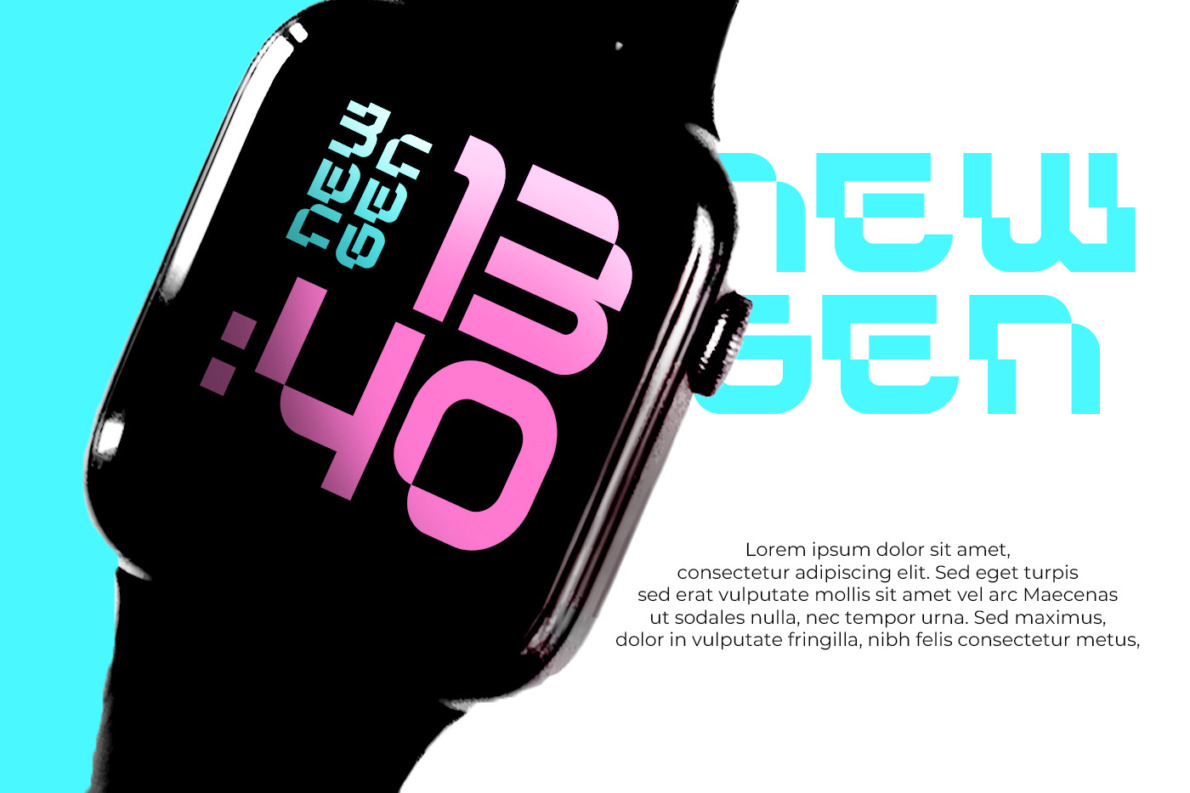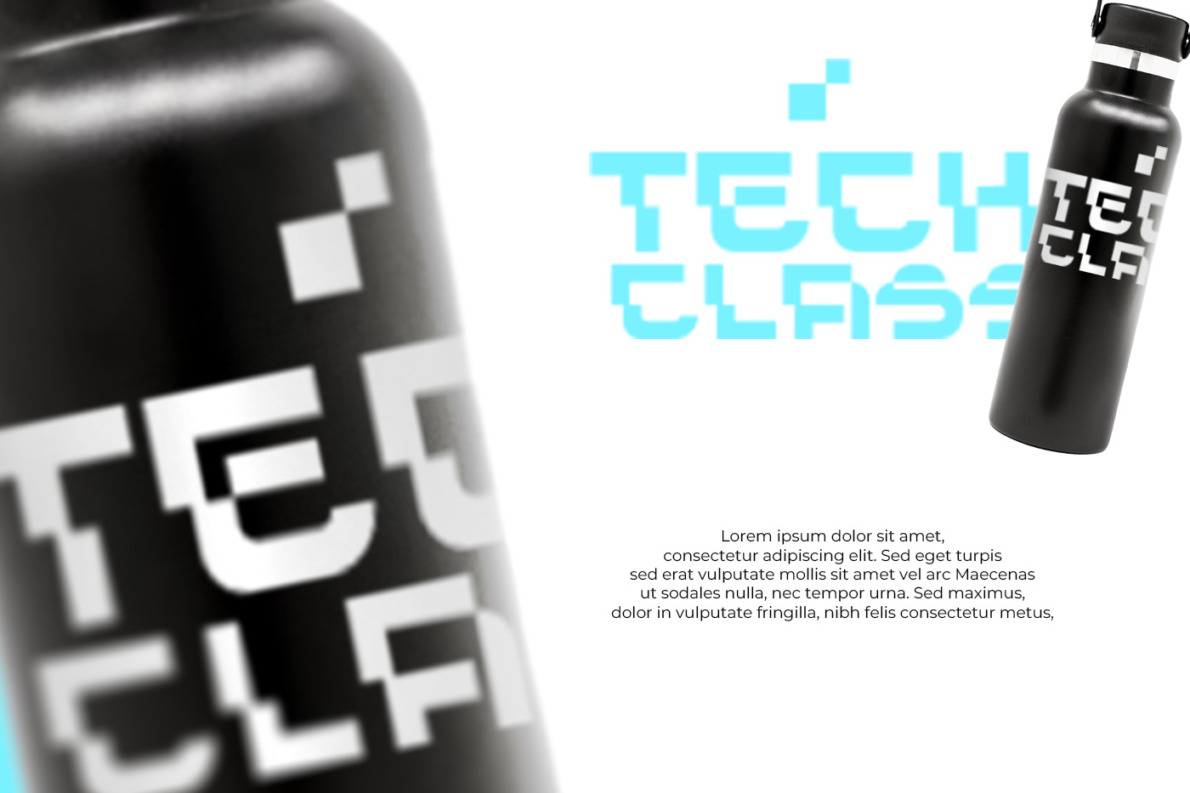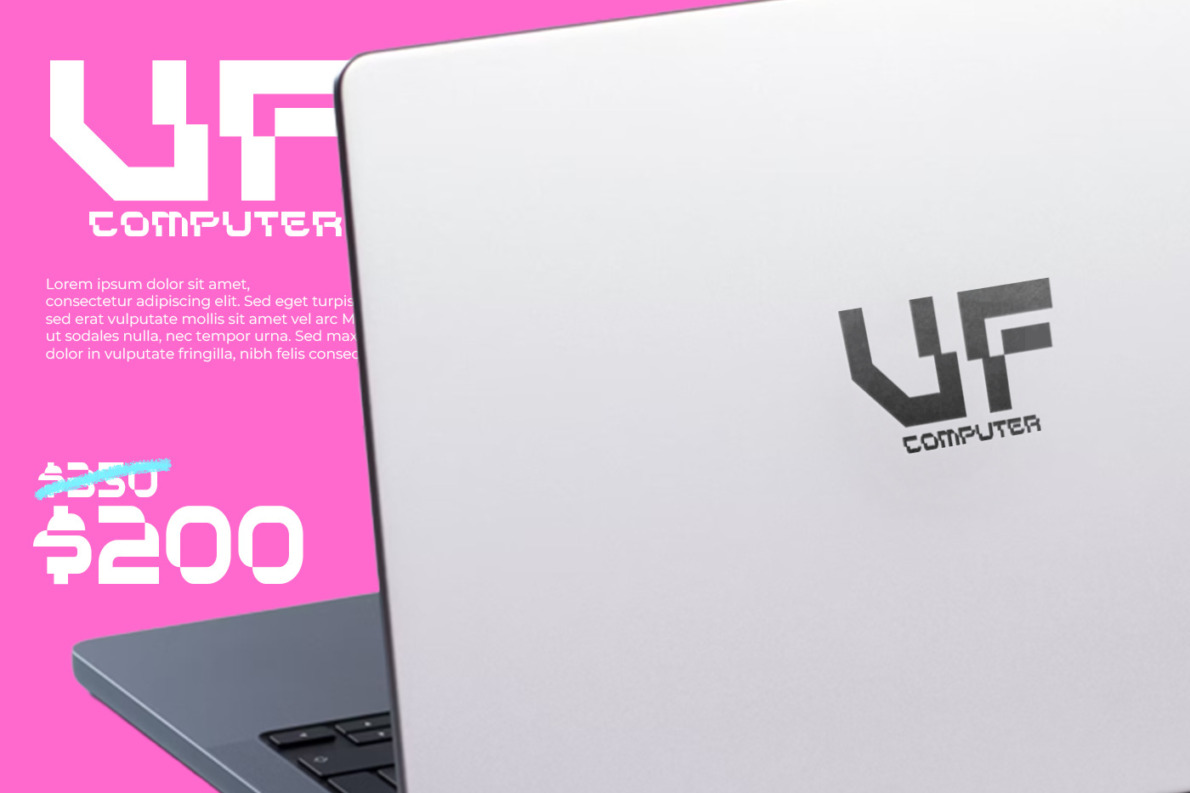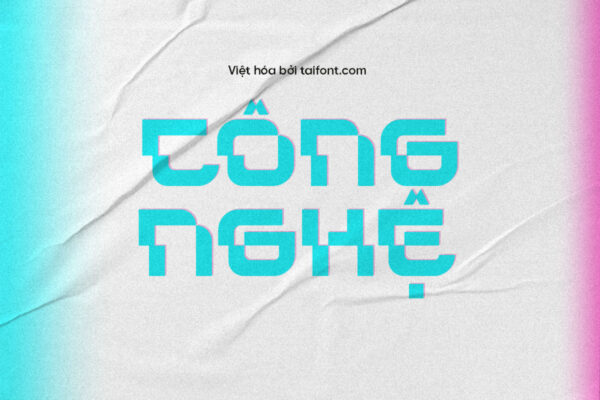
Giới thiệu Font TF Glitech Việt hóa
TF Glitech là một font công nghệ hiện đại được thiết kế với những đường nét táo bạo và phong cách mạnh mẽ, lý tưởng cho các thiết kế liên quan đến tương lai và công nghệ cao. Với kiểu chữ đậm, mạnh mẽ, font này dễ dàng tạo nên một cảm giác tiên tiến, hiện đại và mang hơi hướng khoa học viễn tưởng.
Phiên bản Việt hóa của TF Glitech hỗ trợ đầy đủ dấu tiếng Việt, giúp font dễ dàng sử dụng trong các thiết kế về máy tính, trí tuệ nhân tạo, thiết kế phần mềm, game công nghệ hoặc bất kỳ ứng dụng sáng tạo nào liên quan đến công nghệ.
Nếu bạn đang tìm một font Việt hóa miễn phí mang đậm phong cách công nghệ, TF Glitech chính là lựa chọn tuyệt vời để tạo điểm nhấn cho thiết kế của bạn.
Điểm nổi bật của TF Glitech Việt hóa
Việt hóa đầy đủ dấu tiếng Việt.
Kiểu chữ táo bạo, mạnh mẽ với thiết kế công nghệ.
Lý tưởng cho thiết kế liên quan đến máy tính, trí tuệ nhân tạo và các ứng dụng công nghệ.
Tạo cảm giác hiện đại, sáng tạo và tiên tiến
Font TF Glitech Việt Hóa – Font Công Nghệ Hiện Đại Cho Thiết Kế Tương Lai